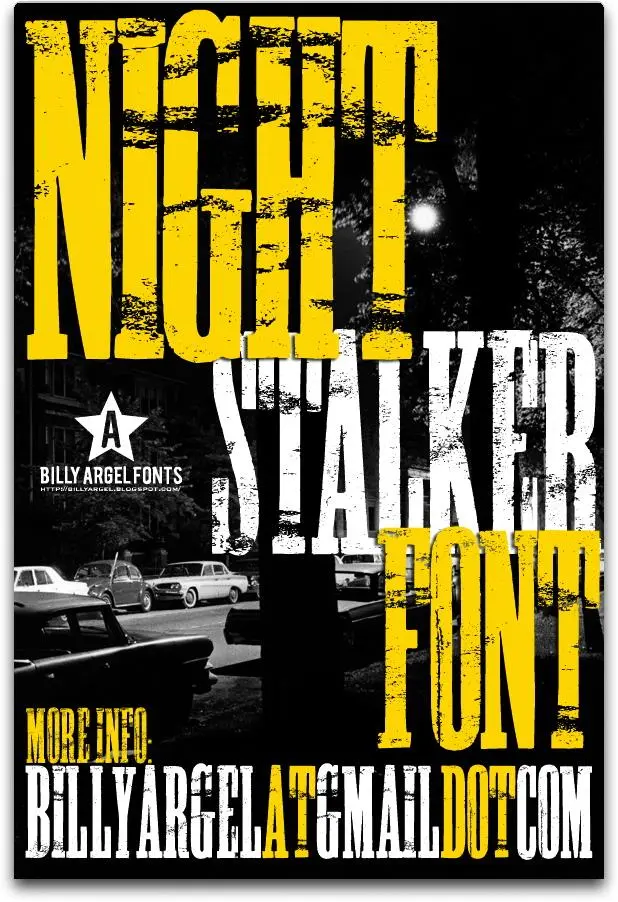
NIGHT STALKER é uma nova adição à família dos gêneros Slab Serif que chegou para transformar os textos em momentos noturnos inquietantes e atraentes. Desenvolvida pelo designer Billy Argel, a NIGHT STALKER se destaca pela sua forma robusta e poderosa, ideal tanto para marcas como para subtítulos de filmes ou capas de livros sobrenaturais. Com linhas grossas e textura marcante, essa fonte captura perfeitamente a atmosfera sombria e intrigada associada ao tema de terror noturno. Ela é uma escolha perfeita para qualquer projeto que exija uma aparência robusta e envolvente, seja ele em um livro de suspense ou no logotipo de uma agência de detetives. Se você está procurando por uma fonte que se destaque como NIGHT STALKER, a garantia é que você não encontrará uma melhor para moldar seu design em temáticas sobrenaturais ou atmosferas noturnas. Com NIGHT STALKER, seu texto ganha vida e presença no meio da escuridão.